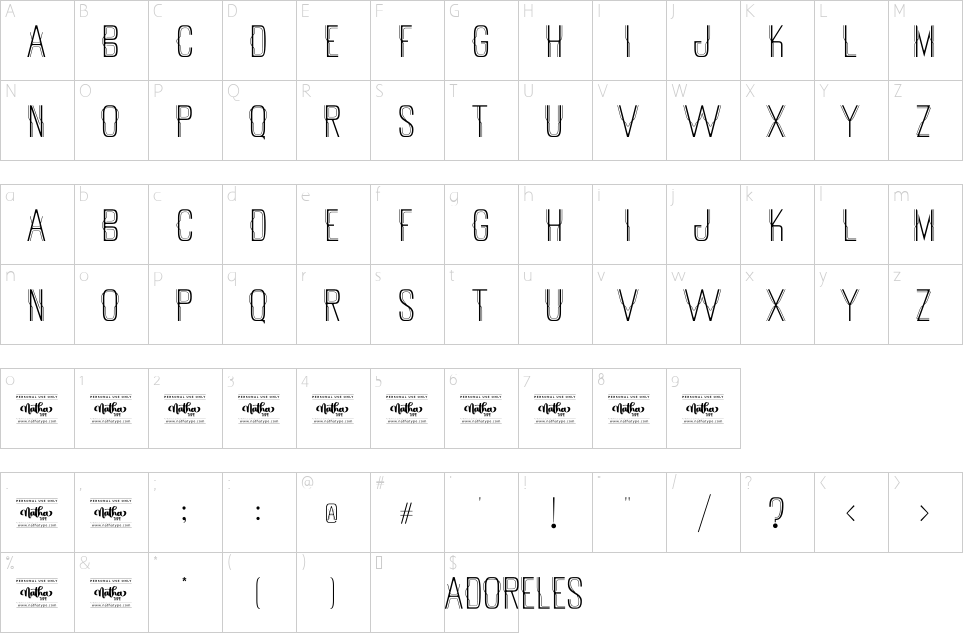
Adoreles é uma fonte elegante e sofisticada, adequada para diversas aplicações gráficas, seja para textos em sites, e-books ou impressões de alta qualidade. Desenvolvida pelo designer Natha Type, esta fonte vem em versões compatíveis com Windows e Mac, permitindo a sua ampla utilização por qualquer entusiasta de design. Com uma aparência minimalista e alegre, Adoreles é perfeita para criar design gráfico minimalista ou para adicionar um toque de diversão e personalidade a projetos. Seja você um designer profissional ou um amante de design que busca uma fonte nova e interessante, Adoreles é uma ótima escolha, já que tem sido baixada por 717 pessoas, demonstrando sua popularidade e qualidade. Descubra por si mesmo a beleza única desta fonte e adote-a para personalizar seus trabalhos com um toque diferenciado.